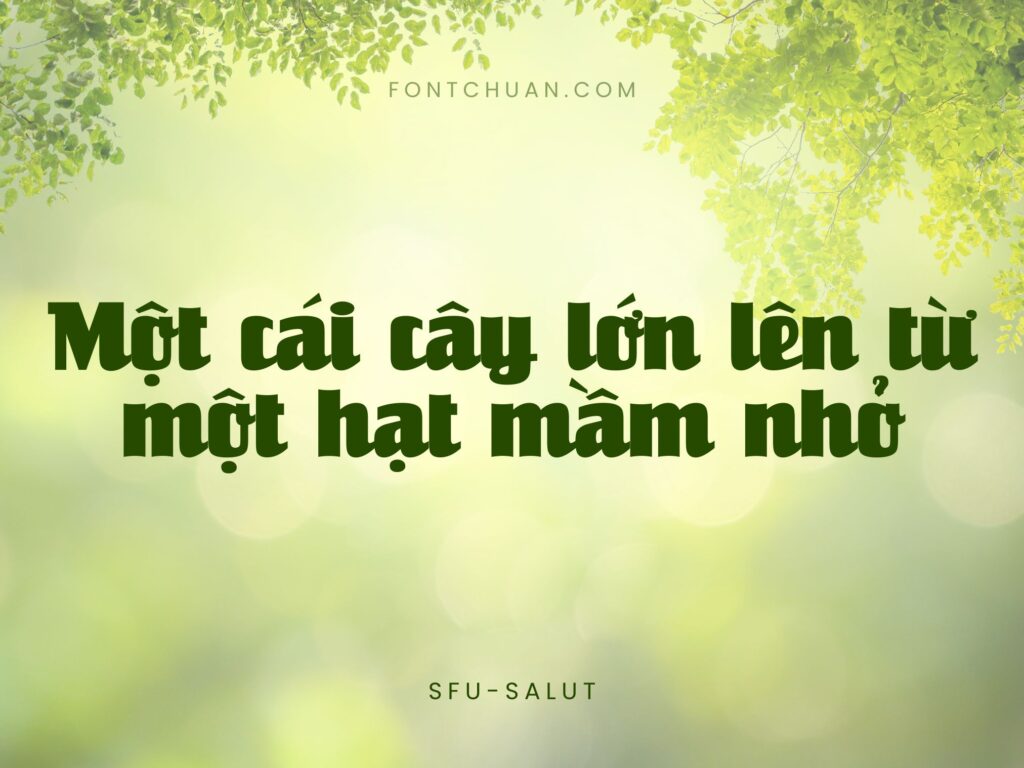
Salut là một kiểu chữ script đậm được thiết kế bởi Heinrich Maehler và phát hành bởi Klingspor vào năm 1931. Với thiết kế độc đáo và phong cách cổ điển, Salut mang lại cảm giác hoài cổ và nghệ thuật, đồng thời rất phù hợp khi được ứng dụng làm Font logo cho các thương hiệu cần sự ấn tượng và khác biệt, hoặc sử dụng như một Font chữ quảng cáo trong các chiến dịch truyền thông để tạo điểm nhấn thị giác mạnh mẽ.
Về mặt thiết kế, Salut nổi bật với các đường nét uyển chuyển và đậm nét, tạo cảm giác mạnh mẽ và thu hút. Font này hỗ trợ nhiều ngôn ngữ và bao gồm các ký tự đặc biệt, giúp người dùng dễ dàng tùy chỉnh theo nhu cầu. Salut thường được sử dụng trong các thiết kế tiêu đề, poster, bao bì sản phẩm và các dự án cần sự nổi bật và phong cách cổ điển. Ngoài ra, Salut còn có thể kết hợp với Font chữ Halloween để tạo ra các thiết kế mang không khí Halloween độc đáo, vui nhộn và ấn tượng, như poster sự kiện, banner hay thiệp chủ đề Halloween. Các ngành nghề như quảng cáo, thiết kế đồ họa và truyền thông có thể tận dụng kiểu chữ này để tạo dấu ấn đặc biệt trong truyền thông.